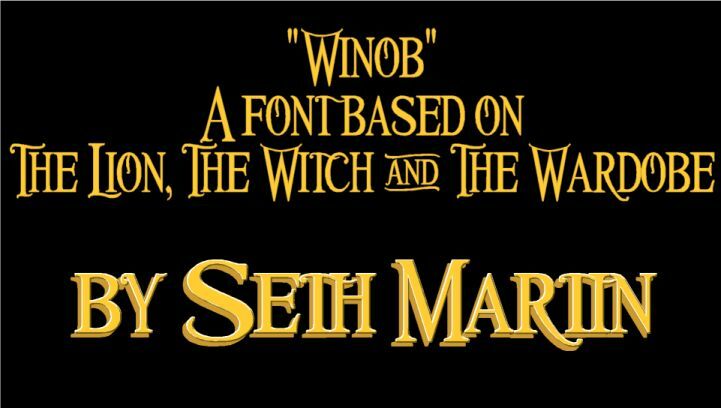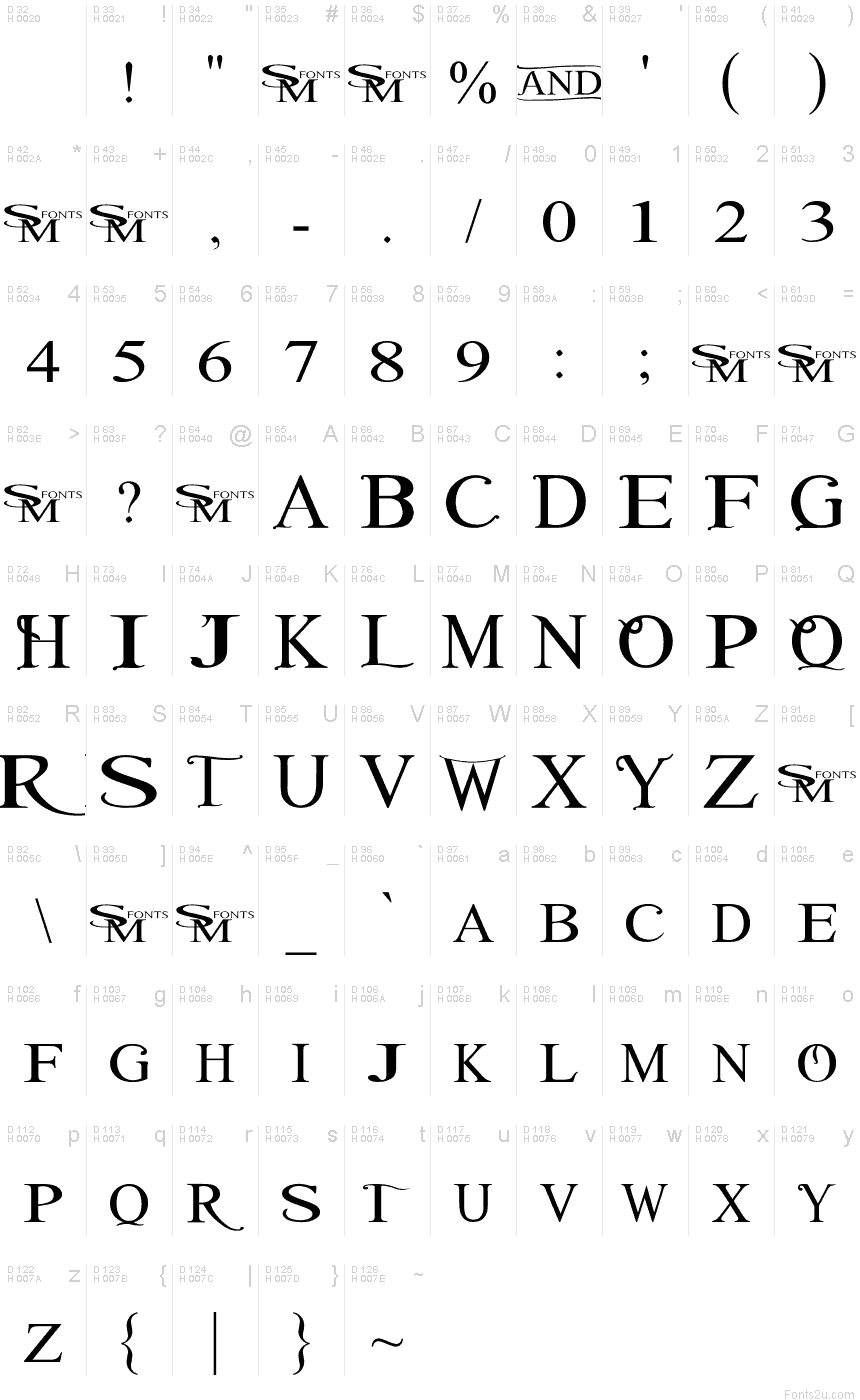
Winob, un font display Art Nouveau gratuito, trasforma le lettere maiuscole con grazie in qualcosa di sontuoso e teatrale. I caratteri appaiono allo stesso tempo scolpiti e ammorbiditi, con verticali arrotondate, grazie larghe a cuneo e una curva interna nella O che conferisce al font un tocco ornamentale, tipico dell'epoca dei poster.
È ideale per poster, copertine di libri, packaging ricercato, titoli e testate dove bastano poche lettere per definire lo stile. Essendo un font gratuito, Winob è perfetto anche per monogrammi e brevi titoli, poiché le sue curve voluminose e i tagli interni eccentrici comunicano con forza anche con poco testo.